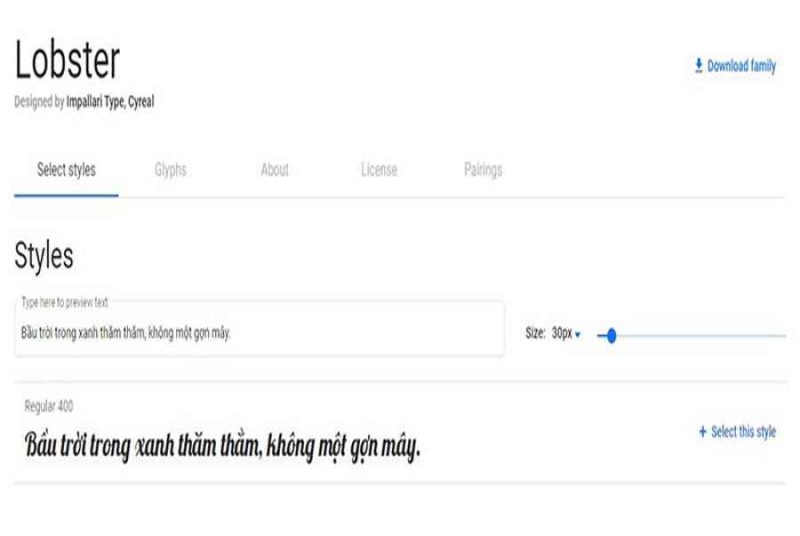
Bài viết sau đây sẽ cung cấp cho bạn những kiểu font chữ tiếng Việt đẹp và đa dụng. Đây là những font chữ được tuyển chọn từ Google Font, đây là kho font chữ miễn phí và có hỗ trợ Tiếng Việt.
I. Font văn bản
1. Be Vietnam
Đây là font chữ đơn thuần với những nét chữ được phong cách thiết kế một cách tối giản nhất, tương thích với mọi loại văn bản .
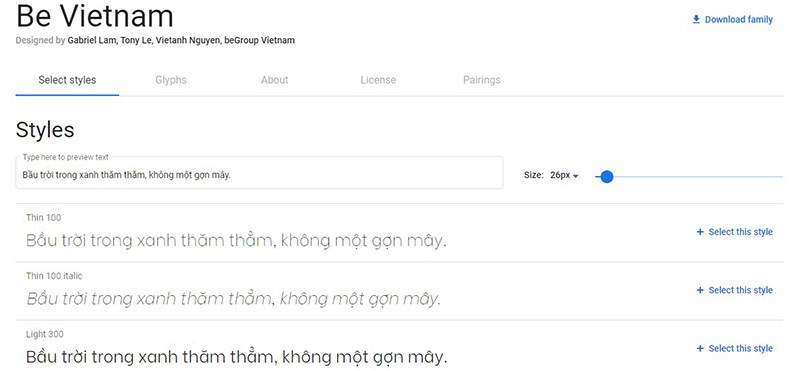
2. Open Sans
Font Open Sans có nét chữ cầu kỳ hơn so với font Be Vietnam, tuy nhiên, 2 font chữ này vẫn khá tương đương về sự đơn thuần, dễ nhìn .
3. Roboto
Font chữ Roboto đơn thuần, khá giống với font Be Vietnam, tuy nhiên, phong cách thiết kế khoảng cách giữa những vần âm của font chữ này có phần dày hơn .
4. Source Sans Pro
Đây liên tục là một font chữ đơn thuần, dễ sử dụng trong soạn thảo văn bản. Font Source Sans Pro khá gọn và dễ nhìn .
5. Playfair Display
Font Playfair Display có phong cách thiết kế nét chữ phong thái hơn so với những font chữ kể trên. Font chữ này tương thích với những văn bản quan trọng .
II. Font thiết kế:
1. Bangers
Bangers là font chữ trộn lẫn giữa những đường kẻ mỏng mảnh và dày một cách liền lạc, tạo ra một font chữ vô cùng phá cách .
2. Lobster
Font chữ Lobster tròn đều, dễ nhìn, rất có thiện cảm với người nhìn. Bạn hoàn toàn có thể dùng font chữ này cho những phong cách thiết kế tiêu đề, banner .
3. Dancing Script
Đây là font chữ bạn nên tìm đến khi cần mô phỏng chữ viết tay .
4. Pacifico
Font chữ này cũng là một lựa chọn tuyệt vời và hoàn hảo nhất khi bạn cần kiểu chữ viết tay. Font chữ này bo tròn và đơn thuần hơn so với font Dancing Script .
5. Bungee Shade
Đây là một font chữ phong thái, tương thích để gây ấn tượng trong những phong cách thiết kế banner, biển hiệu .
6. Saira Stencil One
Font chữ này khá vuông vức và gây ấn tượng mạnh nếu bạn sử dụng trong những phong cách thiết kế tiêu đề, logo loại sản phẩm .
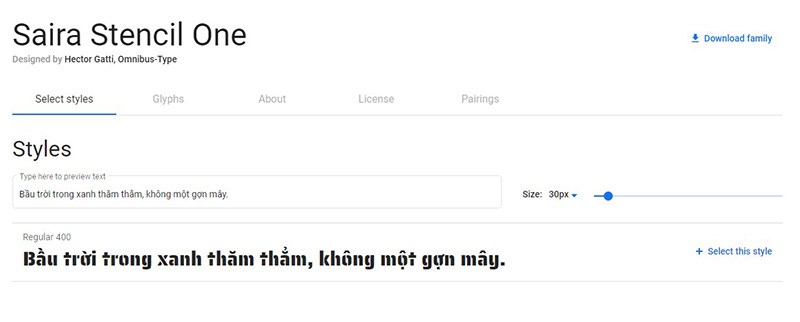
7. Srisakdi
Font chữ này mang đến cho người xem một vẻ bên ngoài vui nhộn với những đường cong lạ mắt. Đây sẽ là điểm nhấn tuyệt vời trong những phong cách thiết kế hạng sang hay những bài viết về chủ đề thời trang và lối sống .
8. Charmonman
Đây là font chữ mềm mịn và mượt mà, sang chảnh. Đây là sự lựa chọn tuyệt đối trong thiết kế xây dựng tên thương hiệu, những bảng hiệu quảng cáo và những bản thiết kế yên cầu sự sang trọng và quý phái .